Display in Use: A Collection of Display Typefaces
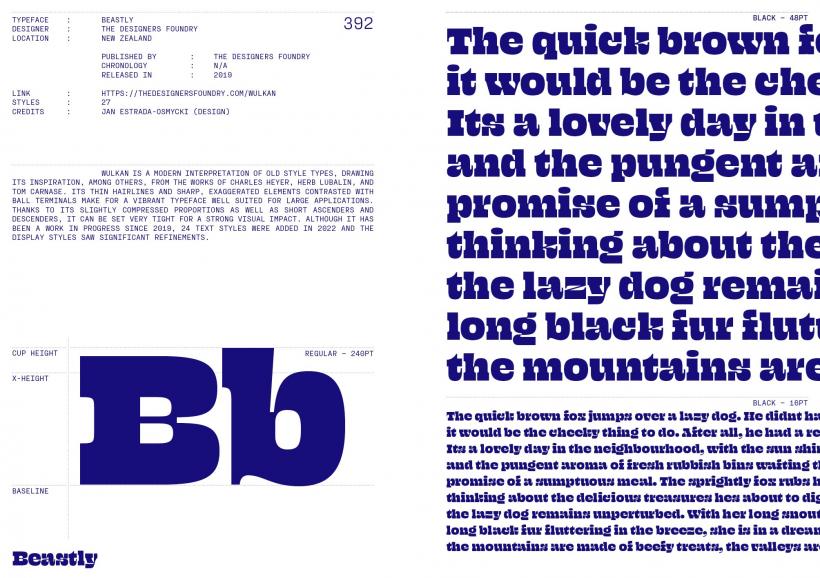
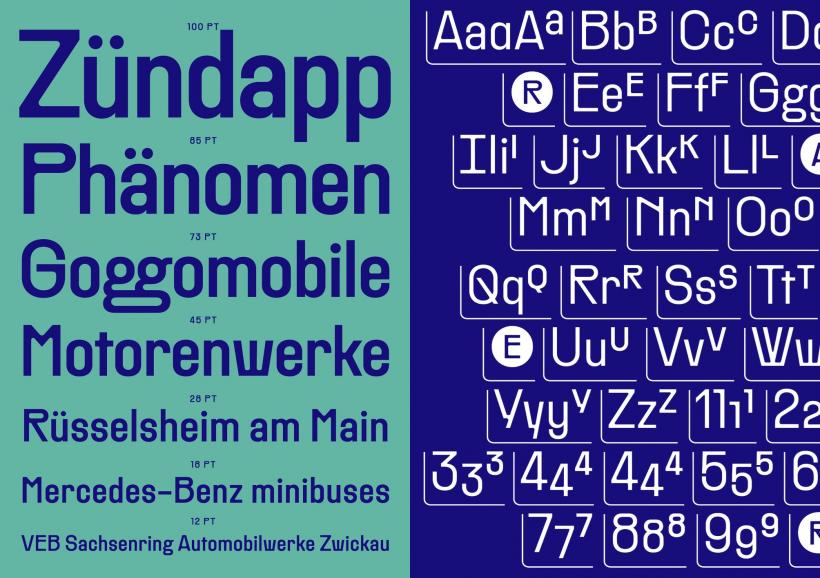
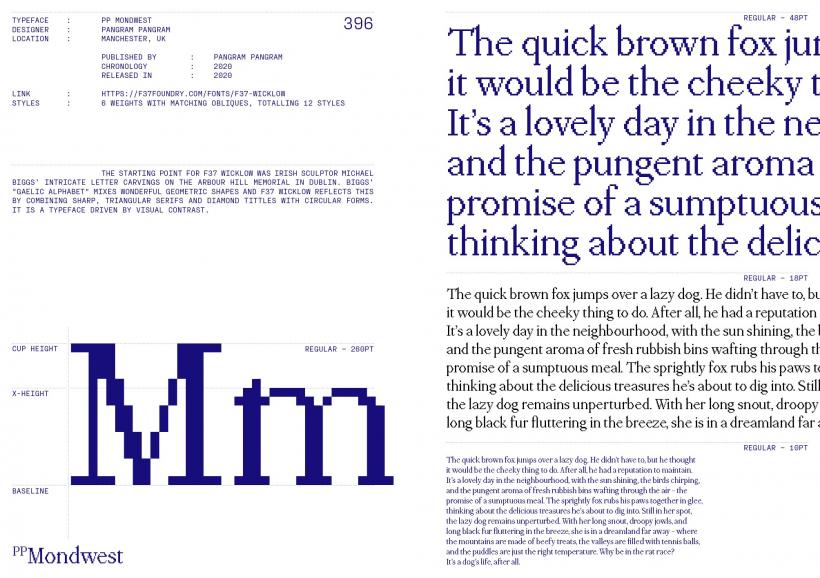
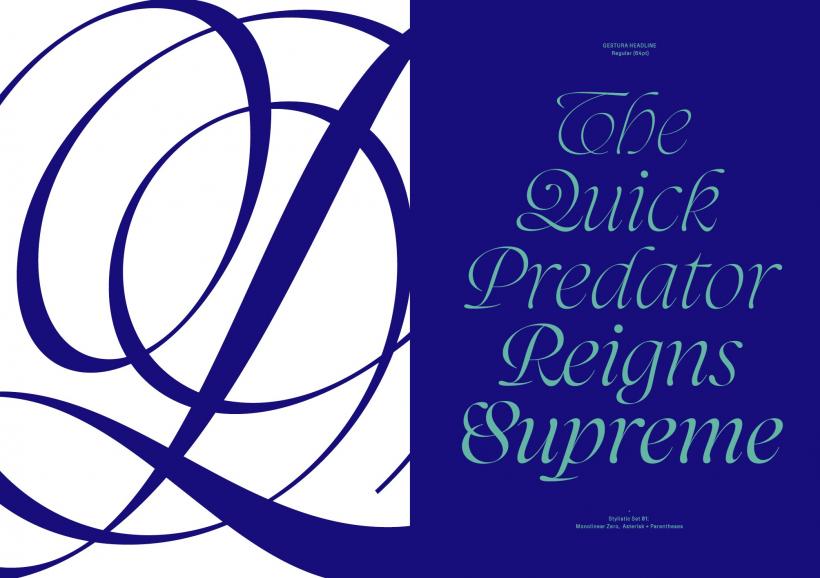
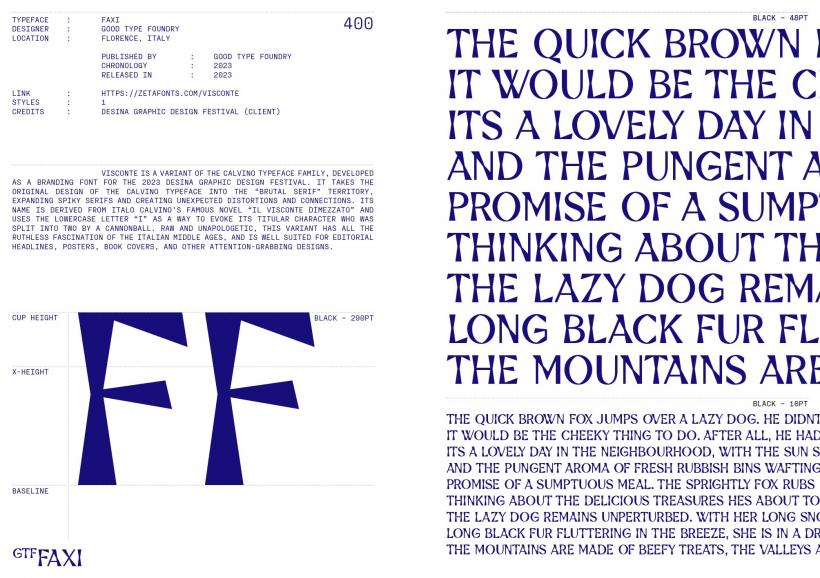
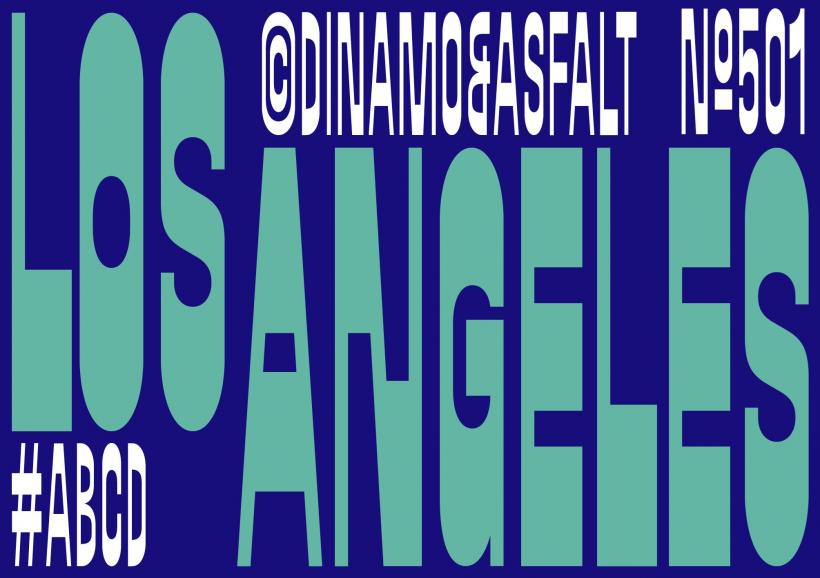
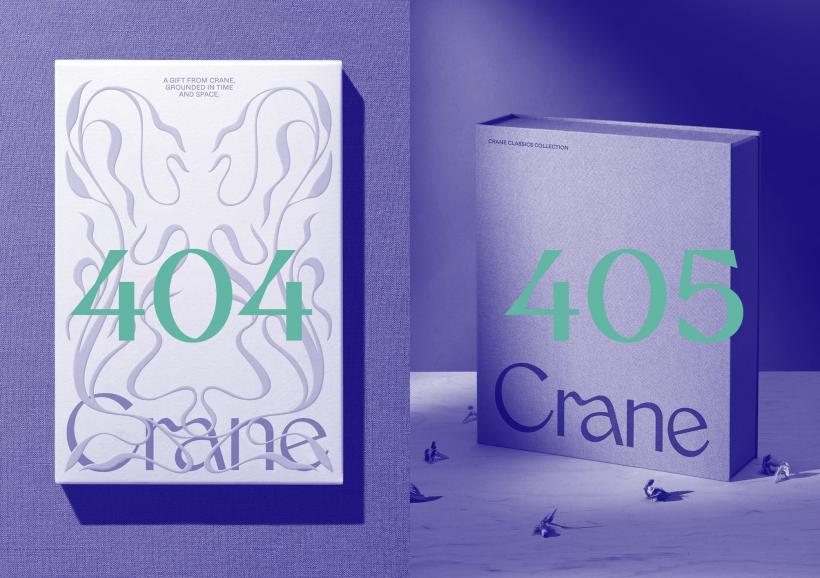
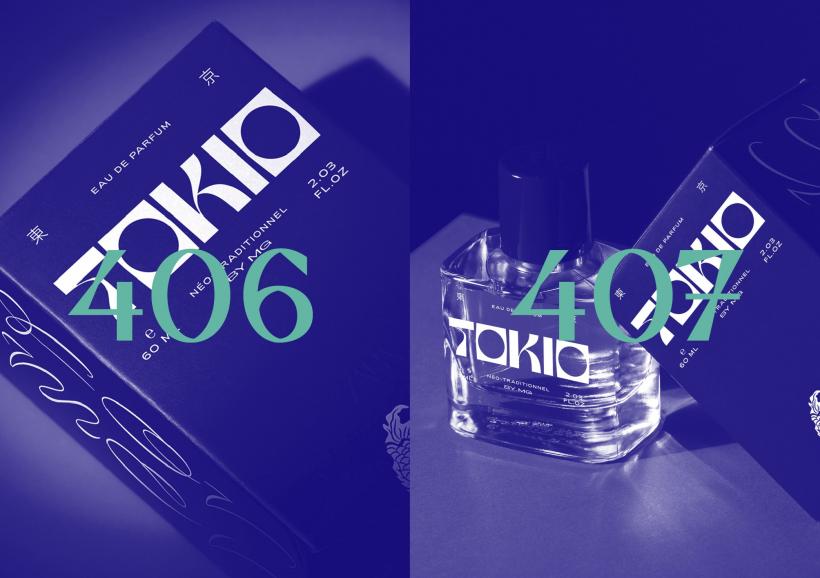
Display in Use зібирає найкращі шрифти для великих полотен і служить орієнтиром для дизайнерів і типографів, які шукають натхнення.
Відомі своїм сміливим характером і привертають увагу, дисплейні шрифти є вибором бренду, якщо він хоче виділитися серед моря конкурентів. Відомі своїми складними деталями, виразним стилем, грайливими елементами та різною вагою, вони адаптуються до різноманітних контекстів дизайну, бездоганно інтегруючись у друковані, цифрові та інші види. Дисплейні шрифти також відіграють вирішальну роль у визначенні індивідуальності бренду та враженнях на перший погляд.
Це видання, яке є продовженням колекції Sans/Sans Serif In Use, містить підібрану колекцію зразків дисплеїв, їх застосування в дизайні та ідеї, які лежать в основі ремесла. Display In Use збирає найкращі гарнітури для великих полотен і служить орієнтиром для дизайнерів і типографів, які шукають натхнення.